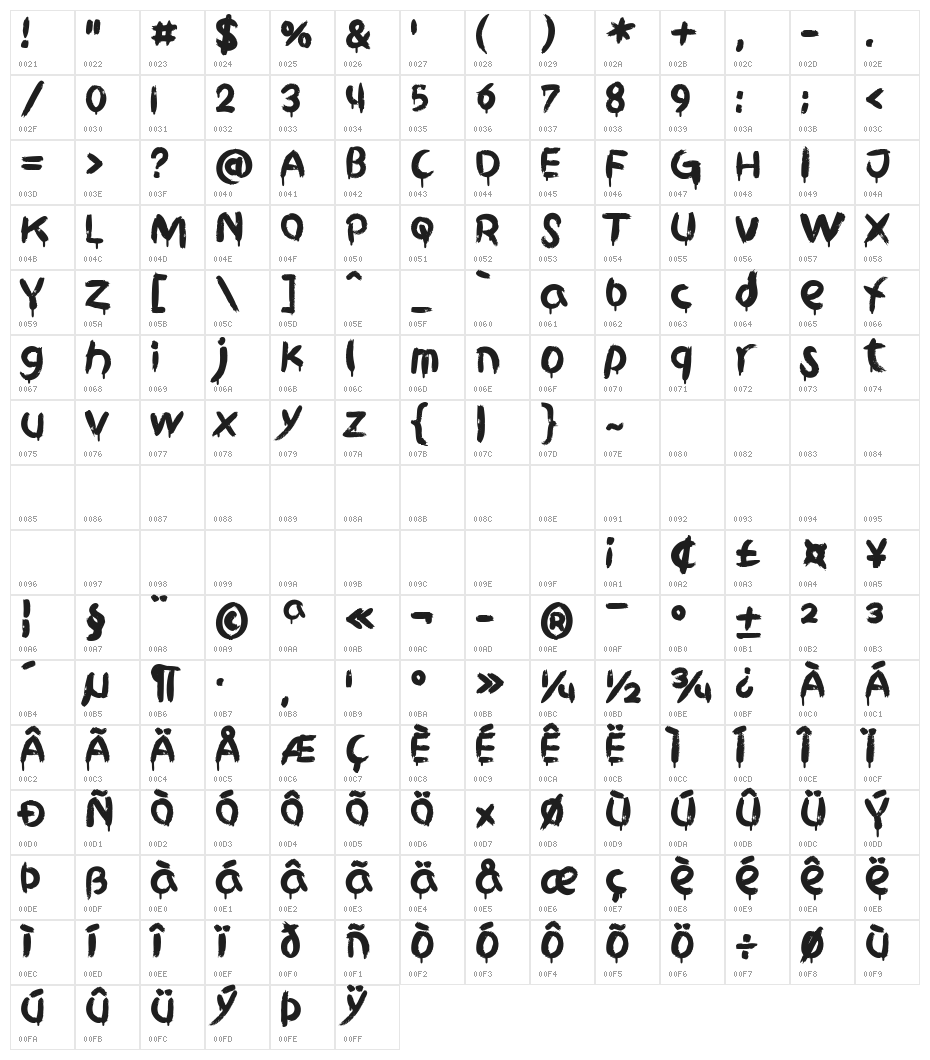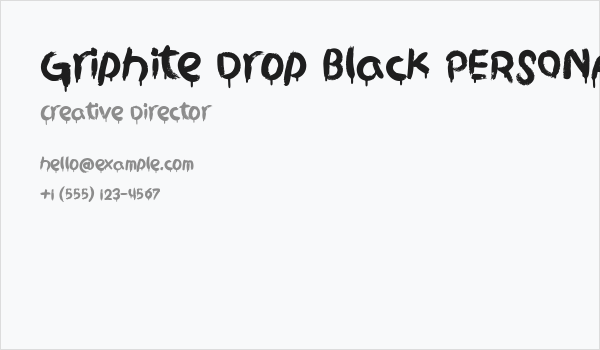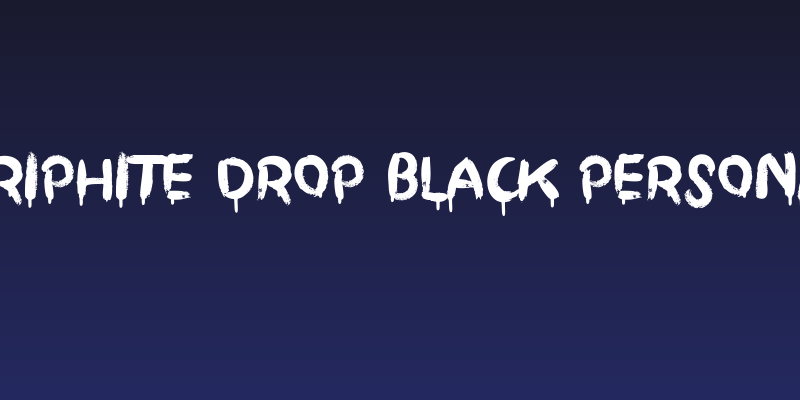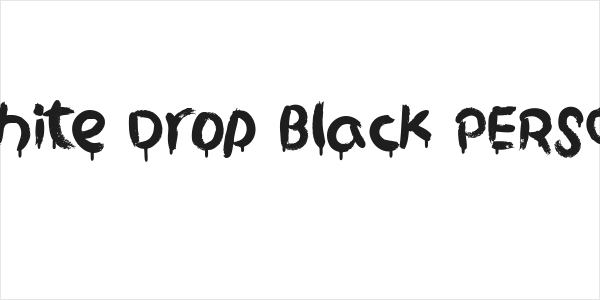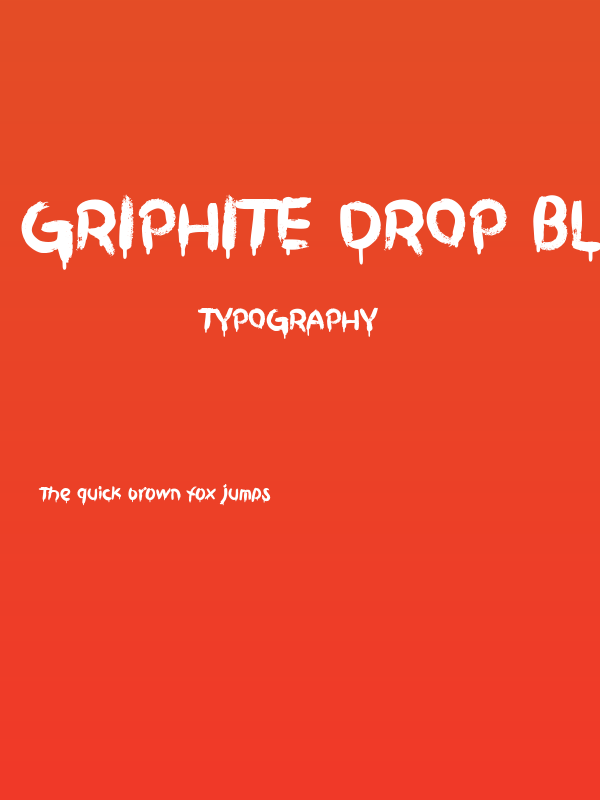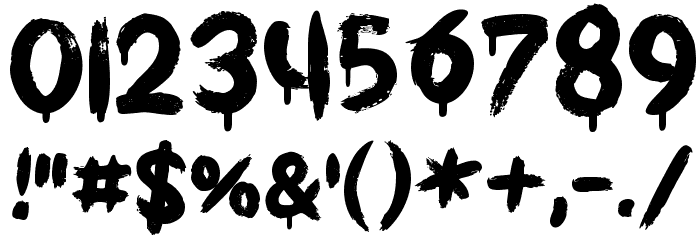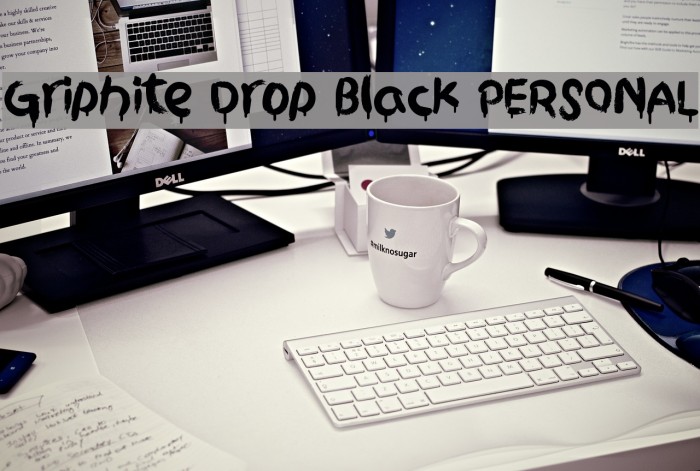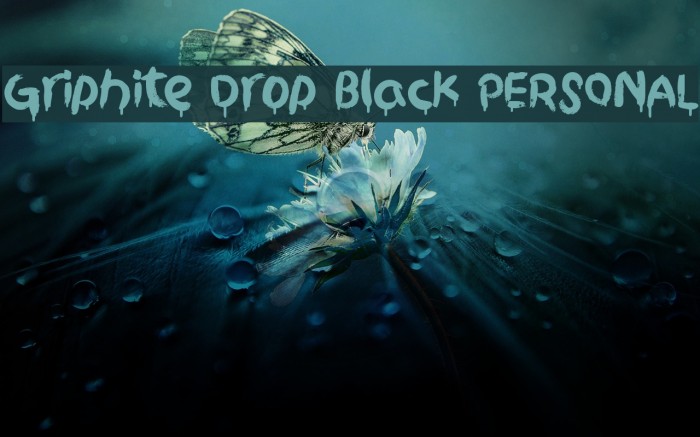
Griphite Drop Black PERSONAL Font
✎ Graffiti
| Estilo general | Urban, Edgy, Artistic |
| Caso de uso | Headlines, Posters, Logos |
| Proyectos propuestos | Perfect for street art designs, music album covers, event posters, and urban-themed branding. |